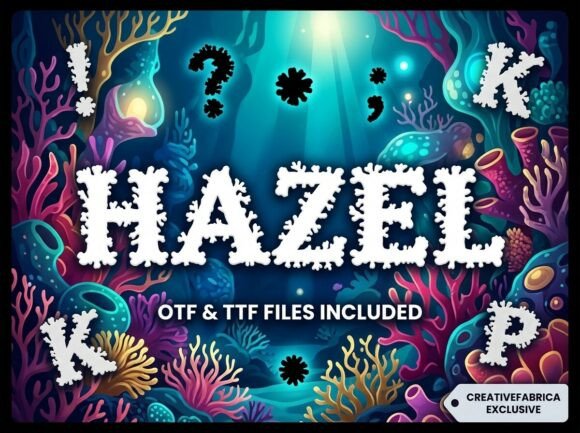
Hazel
Hazel: A Tipografia Subaquática que Transforma Cada Projeto
Se você procura uma fonte que una impacto visual e personalidade oceânica, Hazel é a escolha definitiva. Desenvolvida com texturas orgânicas inspiradas em recifes, plantas marinhas e corais, esta tipografia pesada cria caminhos de letra que parecem esculpidos em pedra viva do fundo do mar. O resultado? Um estilo único que combina a força bruta da natureza com legibilidade impecável.
- Design incomparável: Cada glifo é formado por calcificações de recife e ramificações de coral, proporcionando um visual tridimensional que captura a atenção instantaneamente.
- Leitura clara: Apesar da complexidade dos detalhes, Hazel mantém excelente readability, ideal para títulos, banners e cabeçalhos digitais de alta visibilidade.
- Versatilidade setorial: Perfeita para exposições de aquários, marcas de frutos do mar, cartazes de conservação marinha, embalagens de resorts tropicais, merchandising de estilo de vida costeiro e headlines digitais impactantes.
- Identidade visual marcante: O uso de Hazel confere à sua marca uma assinatura texturizada que evoca a beleza e a força dos oceanos, diferenciando seu conteúdo da concorrência.
- Compatibilidade e desempenho: Otimizada para impressão de alta resolução e para telas modernas, garantindo que os detalhes dos corais permaneçam nítidos em qualquer meio.
Em resumo, Hazel não é apenas uma fonte; é uma experiência sensorial que transporta seu público para um mundo submerso repleto de cor e vida. Se o seu projeto precisa de um toque de marinha com alto impacto visual, escolha Hazel e deixe suas palavras nadarem com elegância e poder.